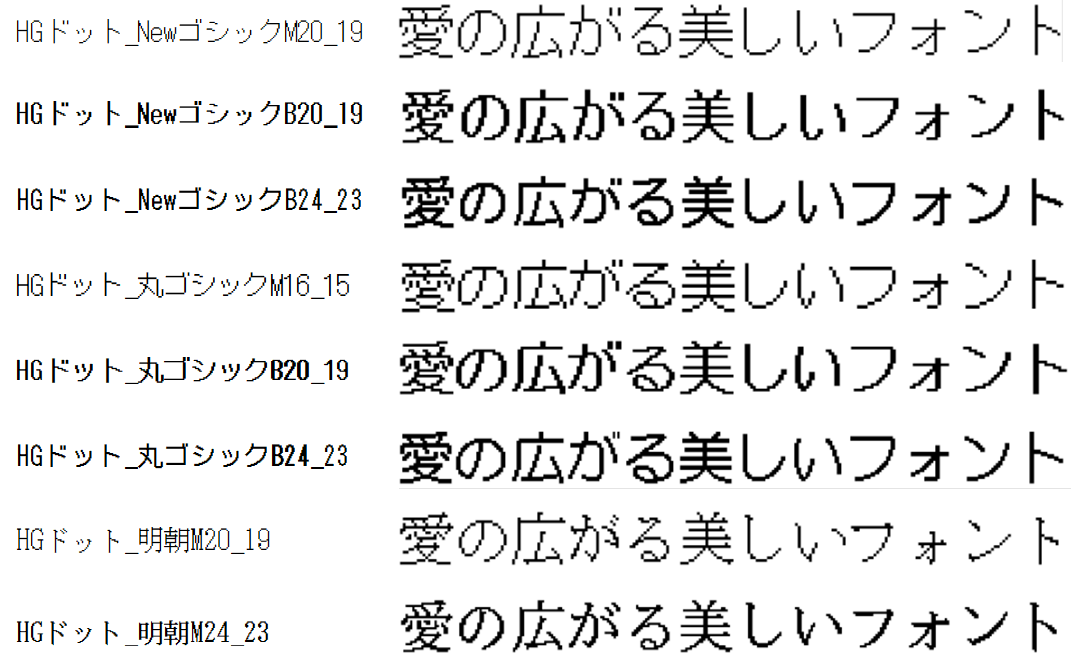
ドットフォント
どうしてドットフォントが誕生したの?
2022年度開催のゲームショウに出展した際にお客様より「もっとサイズ展開したドットフォントが欲しい!」とのお話をいただき誕生いたしました!
こんな方のためにどうぞ
レトロゲームに使いたい
他のゲームと世界観の差別化を図りたい
動画のテロップに使いたい